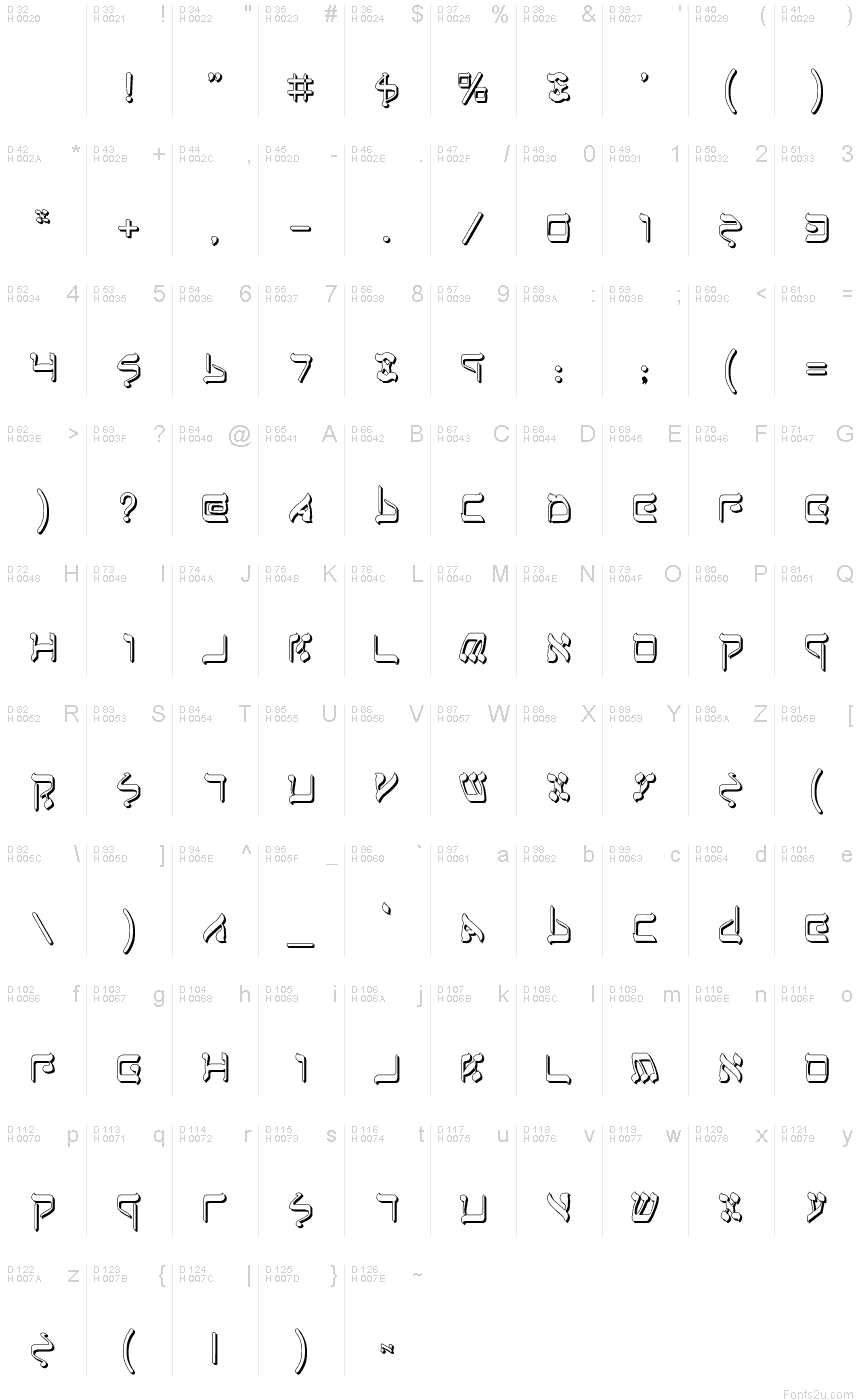
Jerusalem Shadow
Jerusalem Shadow od Iconian Fonts to darmowy, dekoracyjny font typu display inspirowany hebrajskimi formami. Dzięki grubym, rurowym pociągnięciom, zawiniętym końcówkom i wyraźnemu, czarnemu cieniowi wewnętrznemu, każde słowo wygląda jak chromowany napis lśniący w świetle na kamiennej ścianie. Połączenie futurystycznych krzywizn z kaligraficznym rytmem nadaje mu uderzającą, niemal nieziemską formę, która natychmiast przyciąga wzrok w każdym projekcie.
Dzięki Jerusalem Shadow nagłówki sprawiają wrażenie wykutych, a nie tylko wpisanych. Świetnie sprawdzi się w logotypach sci-fi lub fantasy, plakatach tematycznych, interfejsach gier, okładkach książek oraz w brandingu niszowych kawiarni czy marek streetwearowych. Ten darmowy font najlepiej prezentuje się w dużych rozmiarach; w tekście głównym zestaw go z czystym, geometrycznym krojem bezszeryfowym, aby w pełni wyeksponować jego błyszczące, cieniowane kształty.